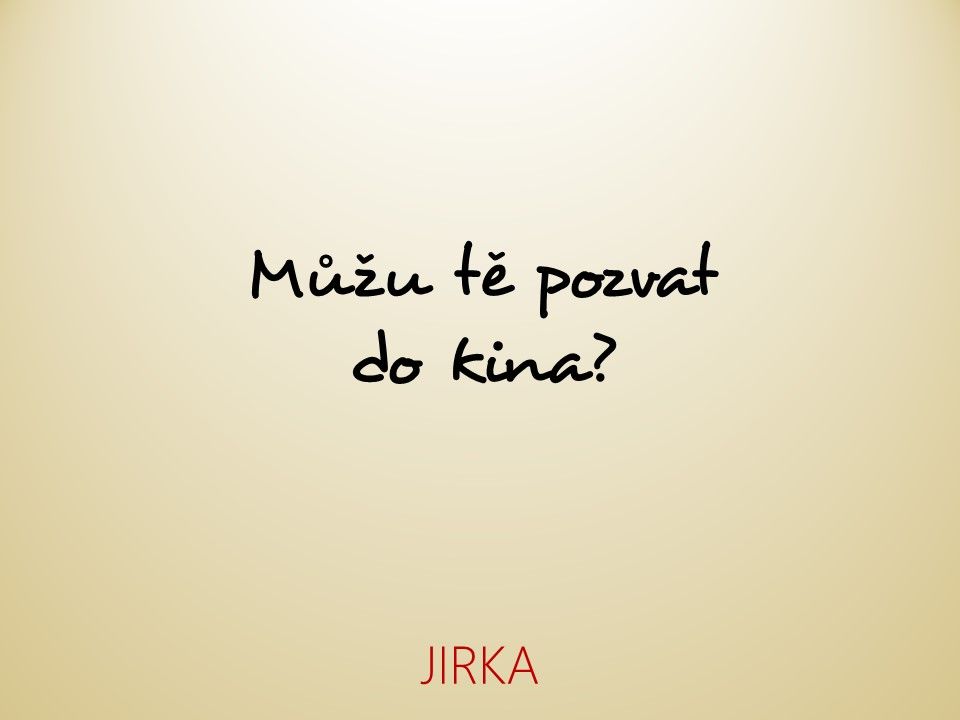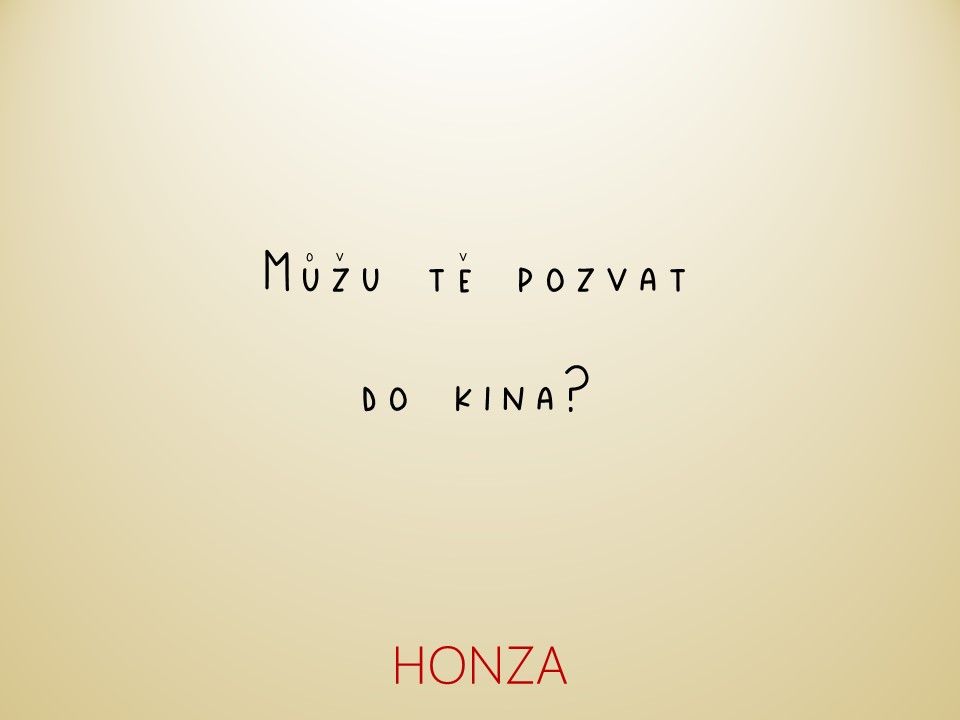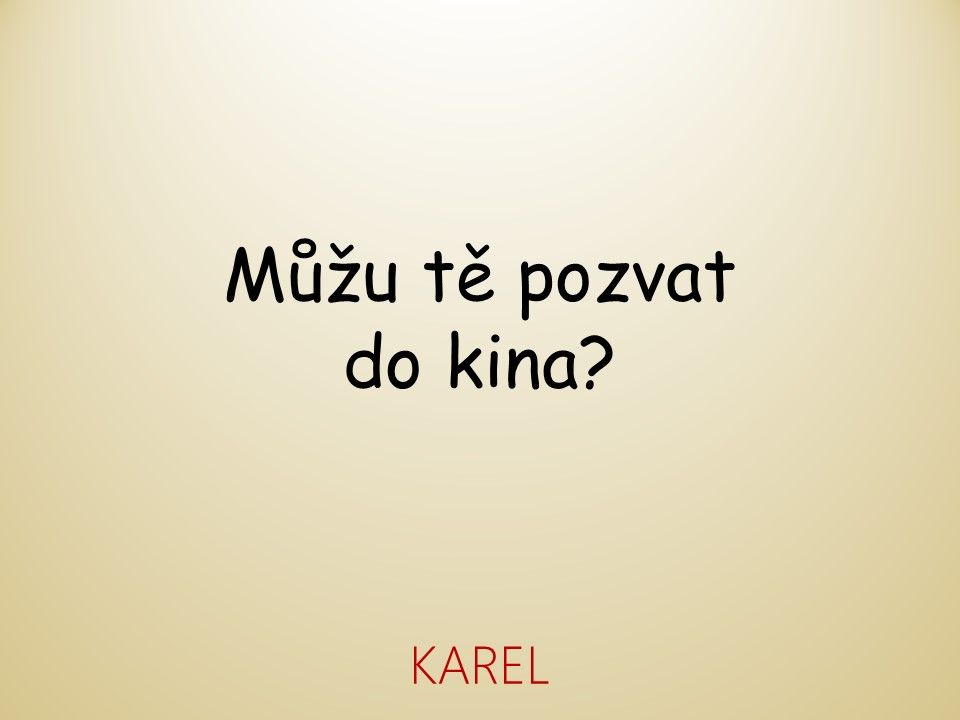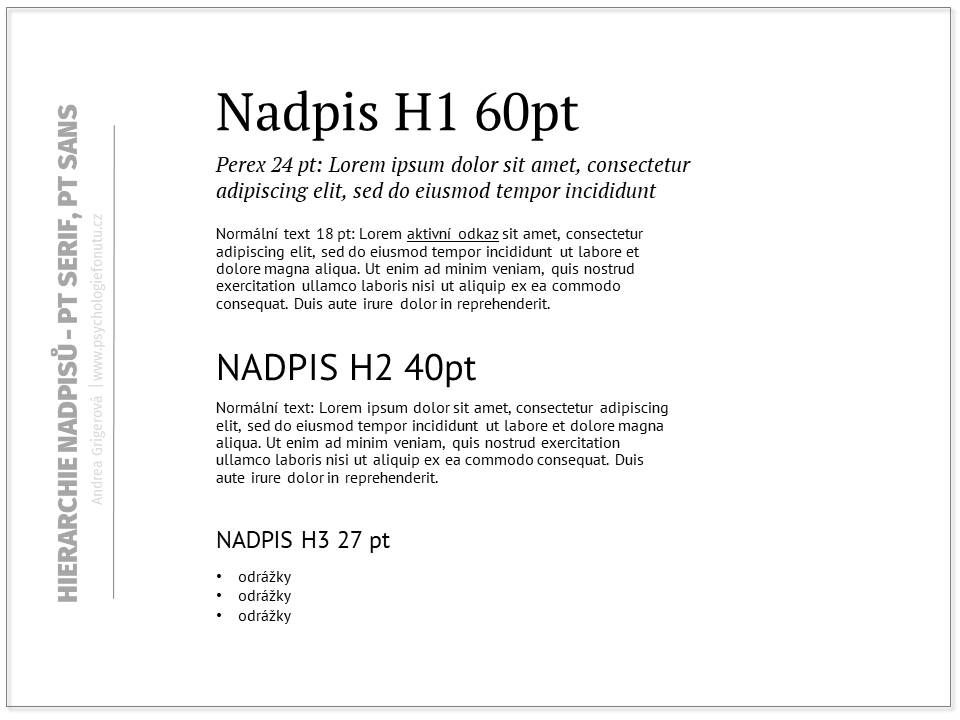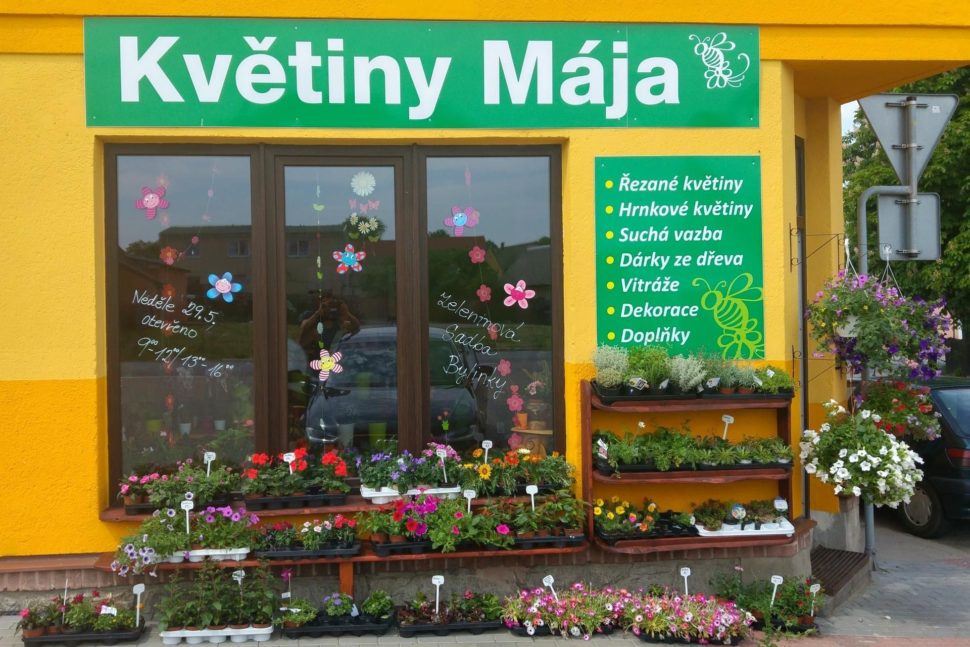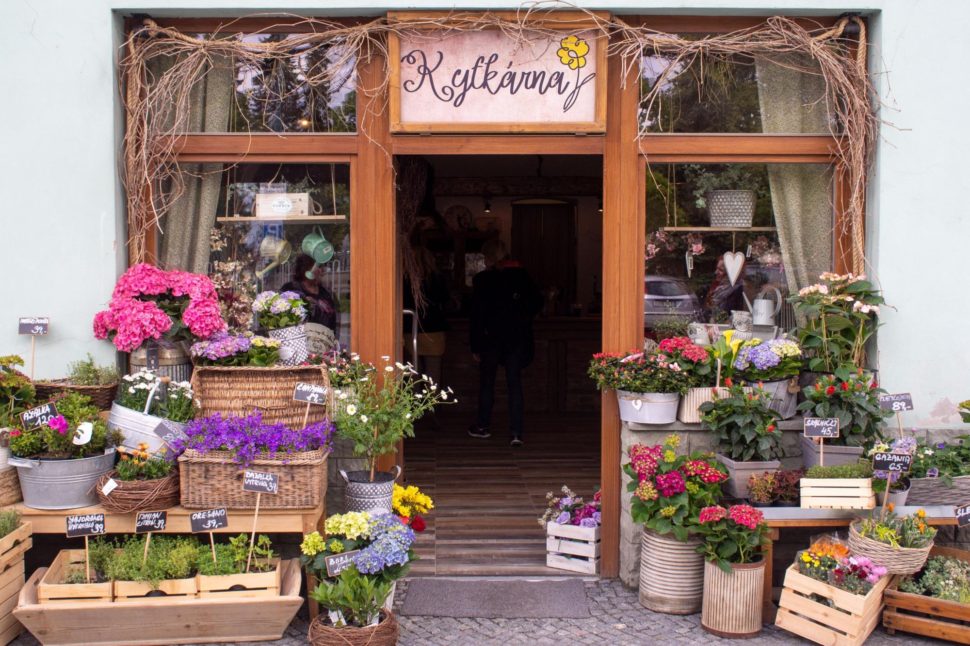
Kdybych to měla shrnout v jedné větě:
Na fontu záleží, jestli lidé u vás nakoupí.
Tak jednoduché to může být. (Samozřejmě za předpokladu, že máte něco kvalitního na prodej.) Ale protože takovému lakonické vyjádření nemusíte věřit, pojďme se na to podívat zblízka.
V čem vám font pomůže?
Zaujmete
Je neoddiskutovatelný fakt, že písmo vyvolává ve čtenáři emocionální odezvu. A to často ještě předtím, než se začte do textu. A velmi často rozhoduje o tom, jestli se do toho textu začte. Vyzkoušejte si to (pánové zapojí fantazii :-)):
S kým byste určitě nešli?
Je to jako pozvánka na rande. Vybíráme si, s kým na to rande půjdeme a vybíráme si i to, jaké texty budeme číst, na jakém webu se zdržíme o trošku déle. A forma, jakou je text prezentovaný, v tomto hraje zásadní roli. Co si budeme povídat, všichni na formu dáme. Záleží nám na tom s kým se bavíme, jak vypadá, jak se chová. A v textu si vybíráme úplně stejně.
Co s tím?
Nematete nepřítele ani klienta
Fonty vám pomohou vést čtenáře tak, aby se v každém okamžiku orientoval kde je, a nezahlcovalo ho spousta balastu, přes který nenajde to důležité.
Je to jako v obchodě. Pokud je přehledný, regály jasně označené, produkty logicky uspořádané, tak je daleko větší pravděpodobnost, že si odnesete to, pro co jste přišli. A pravděpodobně i něco navíc. Na rozdíl od večerky, kde jsou ponožky hned vedle těstovin, využívá se každého volného místa a o označení regálů si můžete nechat jenom zdát. (Proti večerkám jinak vůbec nic nemám, naopak. :-)) Tam schmatnete jenom to, co nutně potřebujete, ovšem za předpokladu, že to najdete.
Co s tím mají společného fonty? Díky fontům je váš web:
Čitelný
Písmo má obrovský vliv na to, jestli se vám bude chtít číst. Tedy, jestli na to nebudete líní. Protože my lidé jsme pohodlní a jakmile větříme námahu, tak hledáme okliku. A když na webu použijete:
- příliš malé písmo
Kdo má ty blechy číst? - příliš komplikované písmo v textu
Jako kudrlinky dobré, ale po jedné dlouhé větě mi splývají do souvislé kudrnaté čáry. - příliš zhuštěné písmo
Nemůžu dýchat! - příliš široké písmo nebo velké mezery
To se táhne jak med, konec v nedohlednu, na to nemám čas… - malé řádkování
Splývá mi to do jedné kompaktní hmoty… - velké řádkování
Tenhle řádek taky patří k tomu odstavci? To mi uniklo, musím si to přečíst znovu dohromady. - příliš tučné nebo tenké písmo v malé velikosti
Obvyklá chyba, pokud se zamilujete do nadpisového fontu a chcete ho napasovat i do odstavců.
tak nás čtení prostě namáhat bude.
Strukturovaný
Prostě musí mít nějakou štábní kulturu. V každé chvíli by měl čtenář a potencionální klient vědět, kde se nachází a kde najde to, co hledá. Takže nezbytností je, ideálně ještě předtím, než se pustíte do psaní, definovat si hierarchii nadpisů a textu a tu pak dodržovat.
Co to znamená definovat si hierarchii nadpisů?
- Napíšete si, jaký font (včetně řezu, velikosti a popřípadě barvy) zvolíte pro H1 nadpisy, jaký pro H2 a jaký pro H3. A to dodržujete. Všude a bez kompromisů.
- Vyberete font a zvolíte velikost písma do textu (hlavní kritérium je čitelnost, aby vám pasoval charakterem a ladil s nadpisy, nad ničím dalším moc nešpekulujte). A to dodržujte. Výjimkou jsou texty jako:
-
- perex (můžete použít kurzívu, nebo větší písmo)
- citáty, motta (můžete použít kurzívu nebo jiný font)
- medailonky, poznámky pod čarou (můžete použít menší velikost písma)
-
- Tímto si pojistíte, že text bude přehledný, jasně definovaná hierarchie dá čtenáři záchytné body při skenování textu a pomůže mu najít co nejrychleji informace, které potřebuje. Navíc to bude vypadat vizuálně přitažlivě.
Uživatelsky přívětivý
Nabízí další záchytné body pro orientaci – nemluvím teď o UX, hierarchii textů nebo stránce s kontakty, ale o tom, že je skvělé používat jednotný systém při zvýrazňování hlavních myšlenek a záchytných bodů v textu. Nejde tedy o nadpisy a členění textu, ale o práci s textem v odstavcích. Když chceme zvýraznit hlavní myšlenku, nemícháme dohromady v jednom odstavci podtržení, tučné písmo a ještě to pro jistotu hodíme do kurzívy… To se pak chováte jako hokynář nebo ukřičený prodejce na trhu.
Jo, a když zvýrazníte v jednom krátkém odstavci 4 hlavní myšlenky, tak se vám může stát, že vynikne právě to, co považujete za nedůležité. Protože čeho je moc, toho je příliš.
Co s tím?
Čitelnost je věda a jestli nechcete, aby vám z webu utíkali dřív, než dočtou první odstavec, tak si přečtěte tento článek.
3. Máte důvěru
Tady se spojují všechny tři body.
- Lidé vám nebudou věřit, pokud si vyberete na web Comic Sans nebo se budete snažit zaujmout nevhodným způsobem.
Co s tím?
Vyberte si font, který bude vycházet ze základních hodnot, přes které ve vašem podnikání nejede vlak. Je to důvěra? Nebo hravost? Anebo minimalismus? Font, který bude jako vaše druhá kůže nebo nejoblíbenější oblečení. Vybírejte takový font, který má šanci oslovit ideálního zákazníka, nebo ho minimálně neodradí.